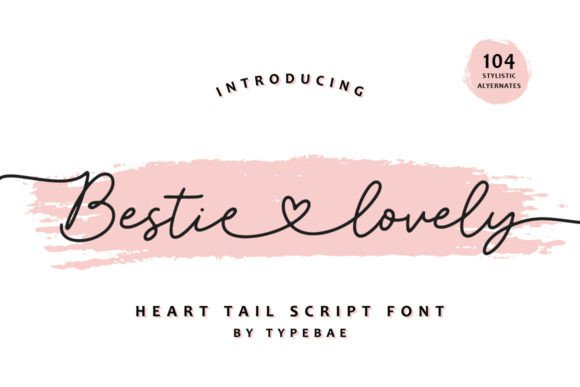
Bestie Lovely
หากคุณกำลังมองหาเนื้อหาคุณภาพสูงเช่น Bestie Lovely แพ็คเกจพรีเมียมนี้เป็นตัวเลือกที่ยอดเยี่ยมสำหรับโปรเจ็กต์สร้างสรรค์ของคุณ
ไม่ว่าคุณจะสร้างผลิตภัณฑ์ POD (Print on Demand) คำเชิญงานแต่งงาน หรือกราฟิกโซเชียลมีเดีย Bestie Lovely ก็เหมาะสมอย่างยิ่ง